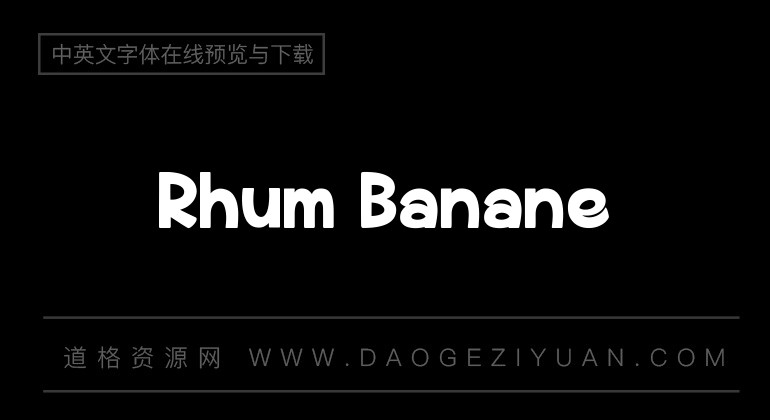
Rhum Banane 是一款温暖粗犷,古朴自然的字体,由法国设计师Matthieu Cortat创作。它的字体风格源自十九世纪的西班牙文字,具有粗犷的行程和宽松的重量,使用它可以让文字有一种温暖的感觉。Rhum Banane 字体的字母具有流畅的线条,可以轻松地与其他字体搭配,使用它可以创造出温暖的氛围。内容介绍
Rhum Banane是一款非常不错的手写艺术字体,具有很好的视觉感,适合于文化类的宣传设计、商业类品牌的广告和产品包装设计以及个性化文字排版等较多场景。